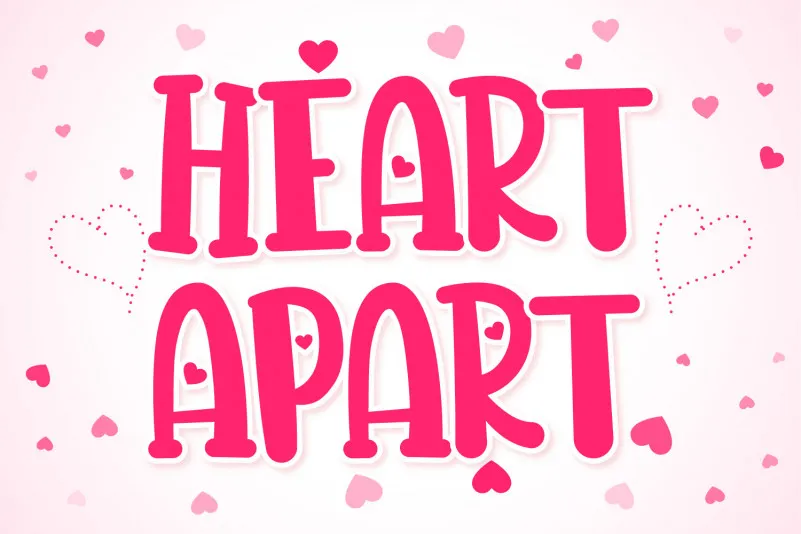
Heart Apart Font – Download Grátis
Heart Apart Font é uma elegante opção para estilos visuais divertidos e espalhafatosos, perfeitamente projetada para levar um toque delicado a qualquer projeto. Ideal para ambientes românticos ou games infantis, essa fonte de exibição foi criada pelo designer Heloyud, com um forte contraste entre linhas grossas e finas que cria uma sensação vibrante. Seja ela usada em cartões de aniversário, gráficos para crianças ou qualquer elemento de design que requer um toque alegre e suave, Heart Apart está pronta para complementar o seu trabalho de forma criativa. Perfect for adding a sweet touch to your projects, whether it be romantic designs or games for children, Heart Apart Font brings together its bold lettering and casual nature beautifully.